Guía de Tipografía Responsiva para Diseño Web Moderno
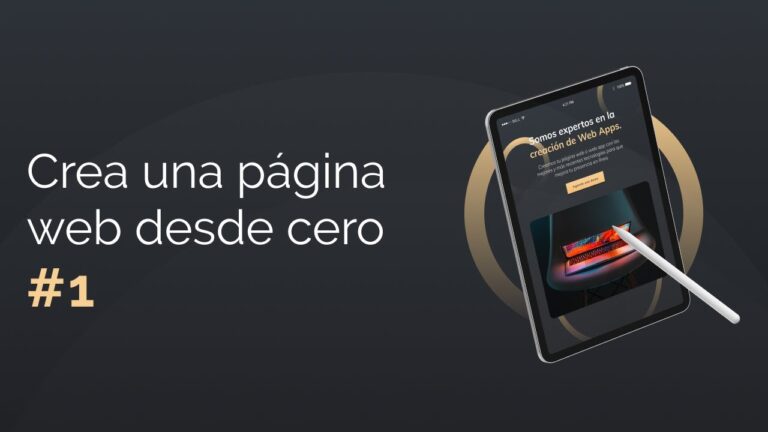
En la era digital actual, la tipografía responsive para web moderna se ha convertido en un elemento esencial para garantizar una experiencia de usuario óptima. En este artículo, exploraremos los fundamentos de la tipografía responsive y cómo implementarla de manera efectiva en tu sitio web para destacar y captar la atención de tus visitantes. ¡Descubre cómo mejorar la legibilidad y el diseño de tu web con las últimas tendencias tipográficas!
- Escoger fuentes adaptables a diferentes tamaños de pantalla
- Utilizar unidades relativas como porcentaje o ems en lugar de unidades fijas
- Probar la legibilidad de la tipografía en distintos dispositivos
- Priorizar la claridad y la accesibilidad en el diseño tipográfico
¿Cuál es la mejor tipografía para página web?
Los ejemplos más populares de fuentes seguras para la web son Arial, Times New Roman y Helvetica. Estas tipografías son ampliamente utilizadas en páginas web debido a su legibilidad y versatilidad. Arial es conocida por su simplicidad y limpieza, Times New Roman por su elegancia clásica, y Helvetica por su modernidad y claridad.
Al elegir la mejor tipografía para una página web, es importante considerar la coherencia con la identidad de la marca y la facilidad de lectura para los usuarios. Las fuentes como Arial, Times New Roman y Helvetica son opciones seguras que garantizan una buena experiencia de lectura en diferentes dispositivos y tamaños de pantalla. Además, estas tipografías tienen una amplia disponibilidad en la mayoría de los sistemas operativos, asegurando una visualización consistente para todos los visitantes del sitio web.
En resumen, la elección de la tipografía para una página web debe basarse en la legibilidad, la coherencia con la identidad de la marca y la disponibilidad en diferentes dispositivos. Arial, Times New Roman y Helvetica son ejemplos de fuentes seguras que cumplen con estos criterios y son ampliamente utilizadas en la web por su versatilidad y calidad en la visualización.
¿Cuál es la tipografía moderna?
Las fuentes modernas se caracterizan por estar basadas en líneas y formas geométricas, lo que les otorga una apariencia limpia, clara y fácil de leer. Con un efecto creativo o un detalle adicional, estas tipografías transmiten una vibra contemporánea y fresca que las distingue de las tradicionales.
¿Qué tipo de tipografía se debe utilizar para los medios digitales?
Lo más recomendable siempre es utilizar fuentes con y sin serifa. Las fuentes manuscritas sorprenden y dan una impresión de movimiento con el que es posible darle un toque personal a la web siempre y cuando se use con moderación. En los medios digitales, la legibilidad es fundamental, por lo que es importante elegir fuentes que sean fáciles de leer en pantallas de diferentes tamaños.
Las fuentes con serifa son ideales para textos largos, ya que ayudan a guiar la vista a lo largo de las líneas de texto. Por otro lado, las fuentes sans serif son más adecuadas para títulos y llamadas a la acción, ya que su diseño limpio y moderno las hace destacar en la pantalla. En general, es importante mantener la coherencia en la elección de tipografías para garantizar una experiencia de lectura agradable y consistente para los usuarios.
En resumen, al elegir la tipografía para medios digitales, es recomendable utilizar una combinación de fuentes con y sin serifa, prestando atención a la legibilidad y coherencia en el diseño. Las fuentes manuscritas pueden aportar un toque personal, pero se deben usar con moderación. Mantener un equilibrio entre la estética y la funcionalidad es clave para asegurar que el contenido sea fácil de leer y atractivo para los usuarios.
Principios de Diseño Tipográfico
El diseño tipográfico es una disciplina que combina arte y técnica para crear composiciones visuales a través del uso de letras y palabras. Los principios fundamentales de este arte incluyen la legibilidad, la coherencia y la jerarquía visual, que permiten comunicar de manera efectiva un mensaje a través de la tipografía. La elección adecuada de tipografías, tamaños, espaciados y colores es esencial para lograr un diseño tipográfico impactante y funcional. Con estos principios en mente, es posible crear piezas gráficas que cautiven al espectador y transmitan el mensaje de manera clara y precisa.
Herramientas para Diseño Web Responsivo
En la era digital actual, es crucial contar con herramientas efectivas para el diseño web responsivo. Una de las herramientas más útiles es Adobe XD, que permite a los diseñadores crear prototipos interactivos y diseños de alta calidad que se adaptan a diferentes dispositivos. Con su interfaz intuitiva y capacidades de colaboración en tiempo real, Adobe XD es una opción ideal para diseñadores que buscan crear experiencias web fluidas y atractivas.
Otra herramienta imprescindible para el diseño web responsivo es Bootstrap, un framework de código abierto que facilita la creación de sitios web y aplicaciones adaptables. Con su amplia gama de componentes y estilos predefinidos, Bootstrap permite a los diseñadores crear interfaces modernas y compatibles con dispositivos móviles de manera rápida y sencilla. Además, su enfoque en la accesibilidad y la usabilidad lo convierte en una opción destacada para proyectos de diseño web responsivo.
En resumen, la tipografía responsive para web moderna es esencial para garantizar una experiencia de usuario óptima en todos los dispositivos. Al elegir fuentes legibles, versátiles y adecuadas para cada pantalla, se puede mejorar significativamente la legibilidad y la estética de un sitio web. Recordar la importancia de la coherencia y la jerarquía en el diseño de la tipografía es clave para transmitir el mensaje de manera efectiva y mantener a los usuarios comprometidos. ¡No subestimes el poder de la tipografía en el diseño web!